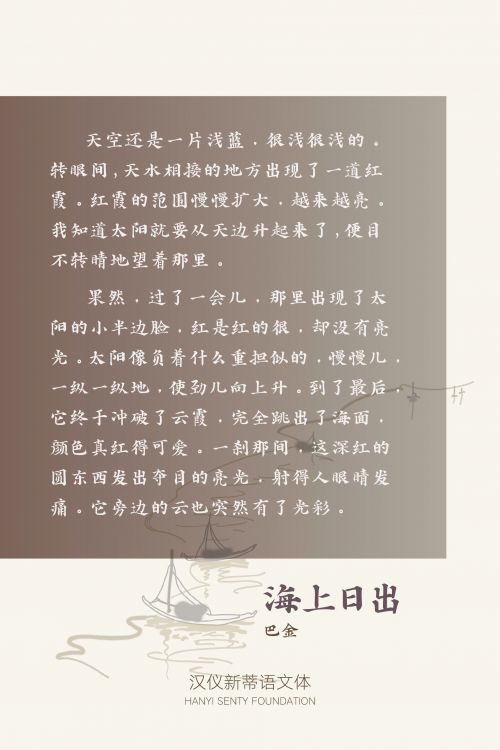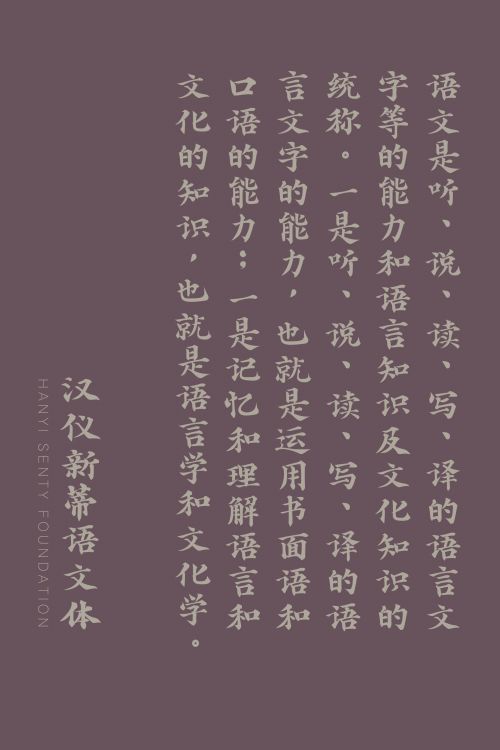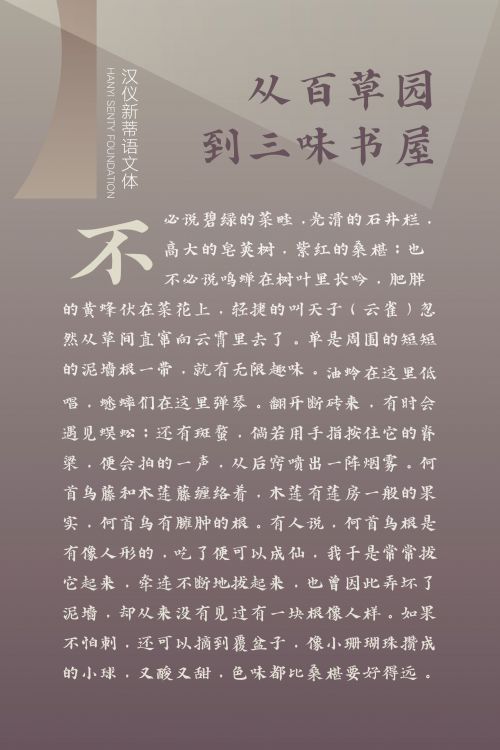
汉仪新蒂语文体
汉仪新蒂语文体的设计与制作本着为学生提供一个具有书写感且符合现代书写规范的参考字体。在目前多数用于识字、语文教学的字体偏向部件化,逐渐脱离的反应真实书写工具,特别是传统毛笔的书写特点,汉仪新蒂语文体提供了一个多元化的选择。汉仪新蒂语文体参考了近代以来一系列手绘语文教材的书法风格,并按照现代书写标准和规范重新设计制作。使得学生在识字、练字的同时,体会传统书写的魅力。